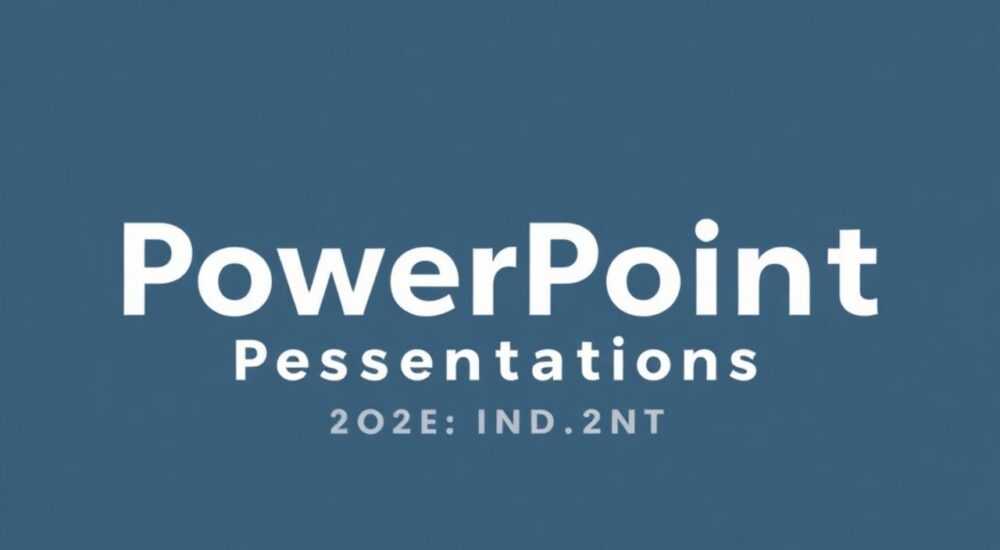
Какой должен быть шрифт в презентации powerpoint
Создание эффективной презентации в PowerPoint требует особого внимания к выбору шрифтов, ведь именно они формируют первое впечатление и влияют на восприятие информации. Многие допускают фатальную ошибку, используя слишком мелкий или сложный для чтения шрифт, что существенно снижает эффективность выступления. Интересно, что согласно исследованиям, правильный выбор типографики может повысить усвоение материала аудиторией на 38%. В этой статье мы подробно разберем, как подобрать идеальный шрифт для презентации, учтем все современные тенденции и технические ограничения.
Основные принципы выбора шрифта для презентаций
Когда речь заходит о создании презентаций PowerPoint, важно понимать базовые правила работы с текстом. Первое правило гласит: размер шрифта должен быть не менее 18 пунктов для основного текста и не менее 24-28 пунктов для заголовков. Это особенно актуально при работе с большими залами, где зрители могут находиться на значительном расстоянии от экрана.
- Выбирайте простые, легко читаемые шрифты без лишнего декора
- Используйте не более двух-трех различных шрифтов в одной презентации
- Убедитесь, что шрифт хорошо смотрится как на светлом, так и на темном фоне
Важно помнить о контрасте между цветом текста и фоном. Исследования показывают, что черный текст на белом фоне обеспечивает лучшую читаемость, однако это не всегда эстетически привлекательно. Поэтому многие профессионалы рекомендуют использовать темно-серый текст на светло-сером фоне – это создает приятное для глаз сочетание.
Технические ограничения и совместимость шрифтов
При работе с PowerPoint необходимо учитывать технические особенности разных устройств и операционных систем. Существует три основных типа шрифтов, которые различаются по способу отображения:
Тип шрифта |
TrueType (TTF) |
Хорошая совместимость Масштабируется без потери качества |
Ограниченная поддержка специальных символов |
OpenType (OTF) |
Поддержка большого количества символов Лучшая масштабируемость |
Может некорректно отображаться на старых системах |
Web-шрифты |
Доступны онлайн Широкий выбор |
Зависят от интернет-соединения Могут быть заблокированы |
Чтобы избежать проблем с отображением презентации на другом компьютере, рекомендуется либо внедрять шрифты в файл PowerPoint, либо использовать стандартные системные шрифты.
Практические рекомендации по выбору шрифтов
Профессиональные дизайнеры презентаций советуют придерживаться следующих практических рекомендаций:
- Для деловых презентаций: Arial, Calibri, Verdana – эти шрифты универсальны и хорошо читаются
- Для креативных проектов: можно использовать более оригинальные шрифты, но только для заголовков
- Для научных докладов: Times New Roman, Georgia – классические шрифты с засечками
Важно отметить, что использование курсива и полужирного начертания должно быть минимальным. Чрезмерное выделение текста может отвлекать внимание и затруднять восприятие ключевой информации.
Экспертное мнение: взгляд профессионала
Александр Константинов, ведущий специалист по корпоративным презентациям с 15-летним опытом работы и автор более 500 успешных проектов для крупных компаний, делится своим опытом:
«За годы работы я вывел несколько важных принципов работы со шрифтами. Во-первых, никогда не используйте больше трех различных шрифтов в одной презентации – это создает эффект ‘типографического хаоса’. Во-вторых, помните о ‘правиле семи’: не более семи строк текста на слайде и не более семи слов в строке. Особенно хочу отметить важность тестирования презентации на разных устройствах перед выступлением.»
Из личного опыта Александра: однажды он столкнулся с ситуацией, когда презентация для крупного клиента отображалась некорректно из-за использования нестандартного шрифта. С тех пор он всегда проверяет совместимость всех элементов на нескольких устройствах заранее.
Частые вопросы про шрифты в PowerPoint
- Какой минимальный размер шрифта считается допустимым?
Для основного текста – 18pt, для заголовков – 24-28pt. Однако лучше стремиться к использованию шрифтов размером 24pt и выше. - Можно ли использовать собственные шрифты?
Да, но необходимо помнить о возможных проблемах с отображением на других компьютерах. Лучше либо внедрить шрифты в презентацию, либо выбрать стандартные варианты. - Как проверить читаемость шрифта?
Проведите простой тест: отойдите от экрана на 2-3 метра и попробуйте прочитать текст. Если возникают трудности – шрифт слишком мелкий или сложный. - Сколько цветов текста можно использовать?
Рекомендуется использовать не более двух-трех цветов, чтобы не перегружать восприятие. Основной текст должен быть одного цвета, выделения – другого. - Как быть с многоязычными презентациями?
Выбирайте шрифты, поддерживающие необходимые языковые символы. Убедитесь, что все используемые языки одинаково хорошо читаются.
Современные тенденции в типографике презентаций
С развитием технологий появились новые возможности для работы со шрифтами в PowerPoint. Например, функция «Designer» автоматически подбирает гармоничные сочетания шрифтов и цветов. Также стали доступны адаптивные шрифты, которые автоматически подстраиваются под размер экрана.